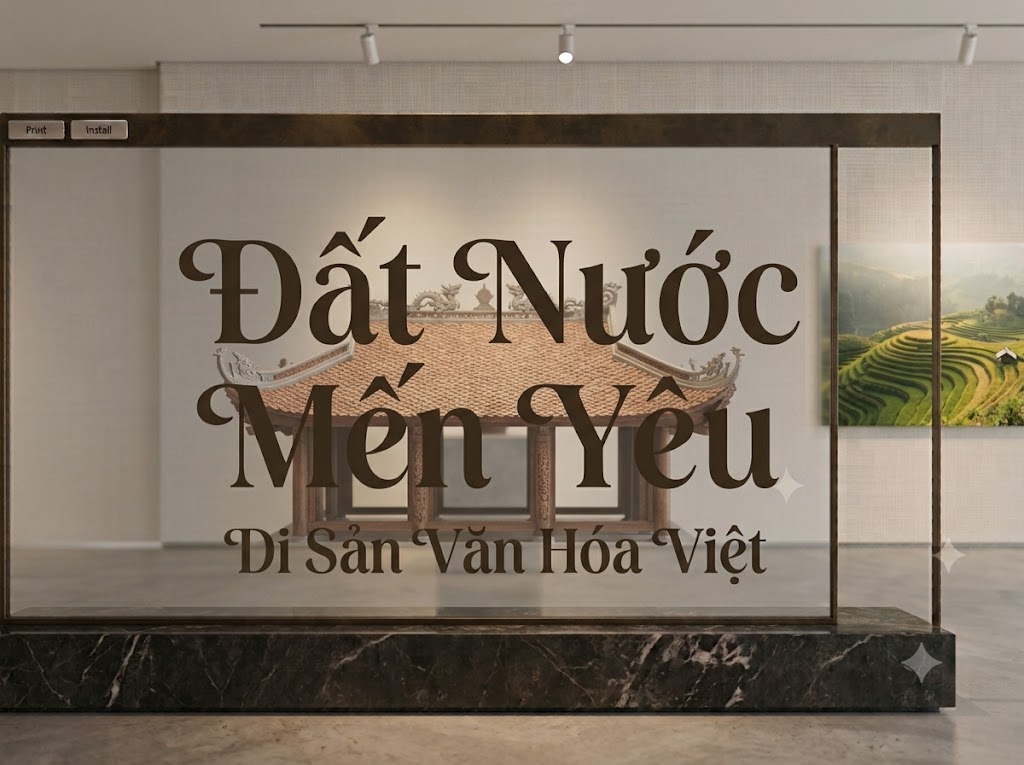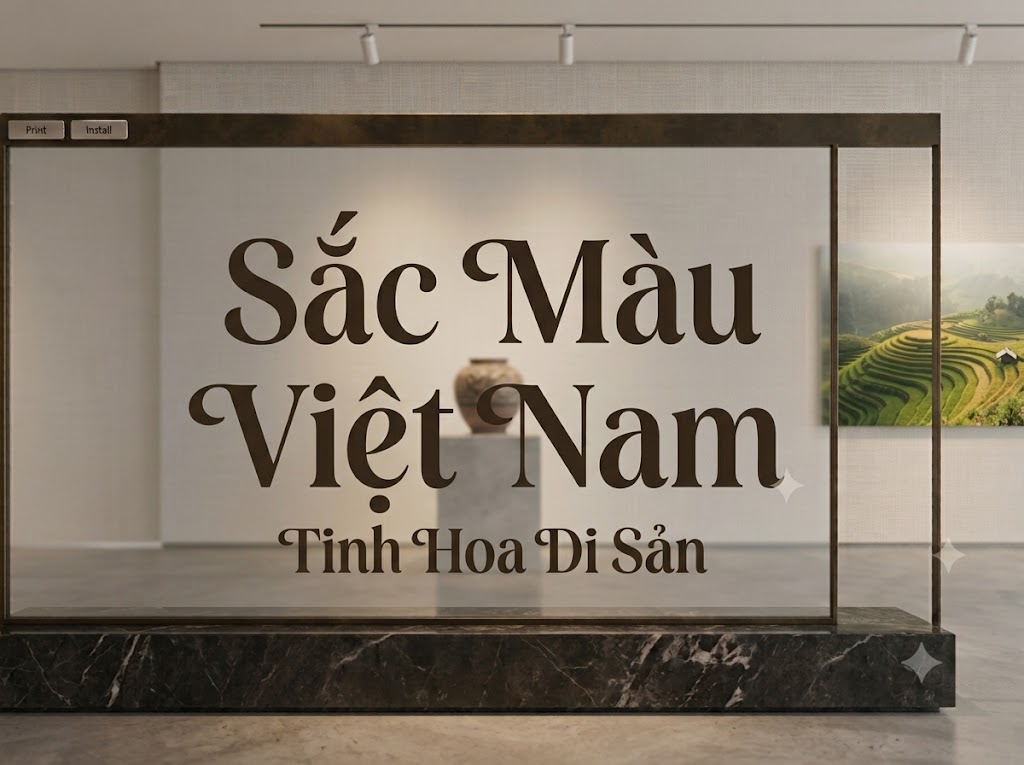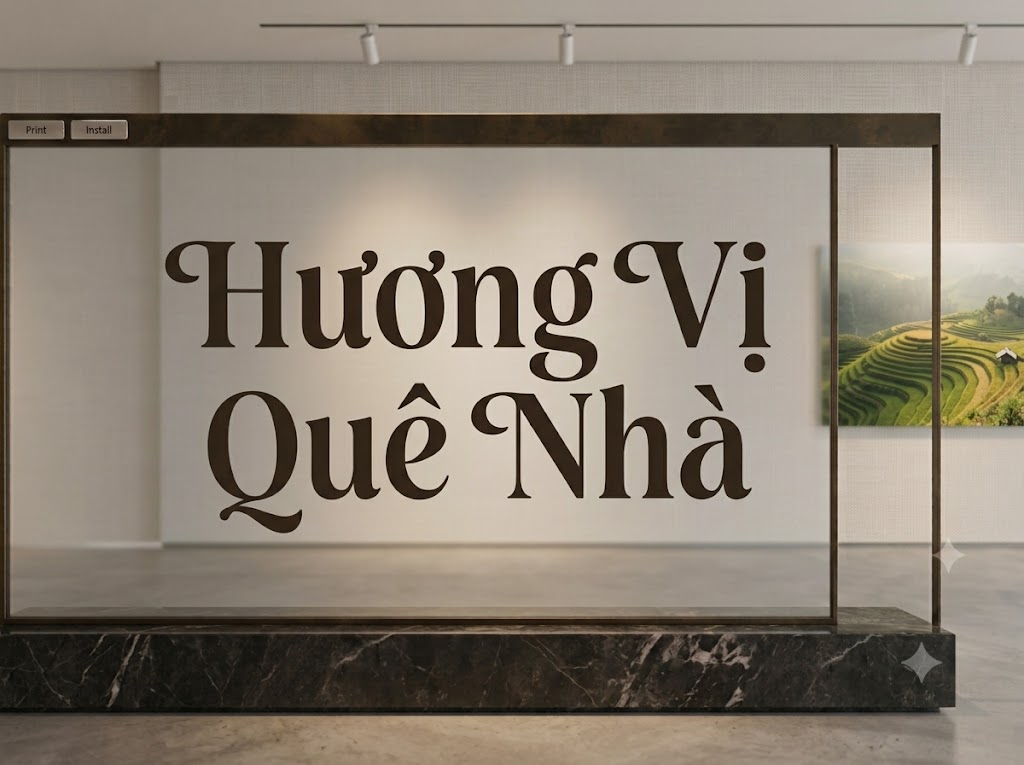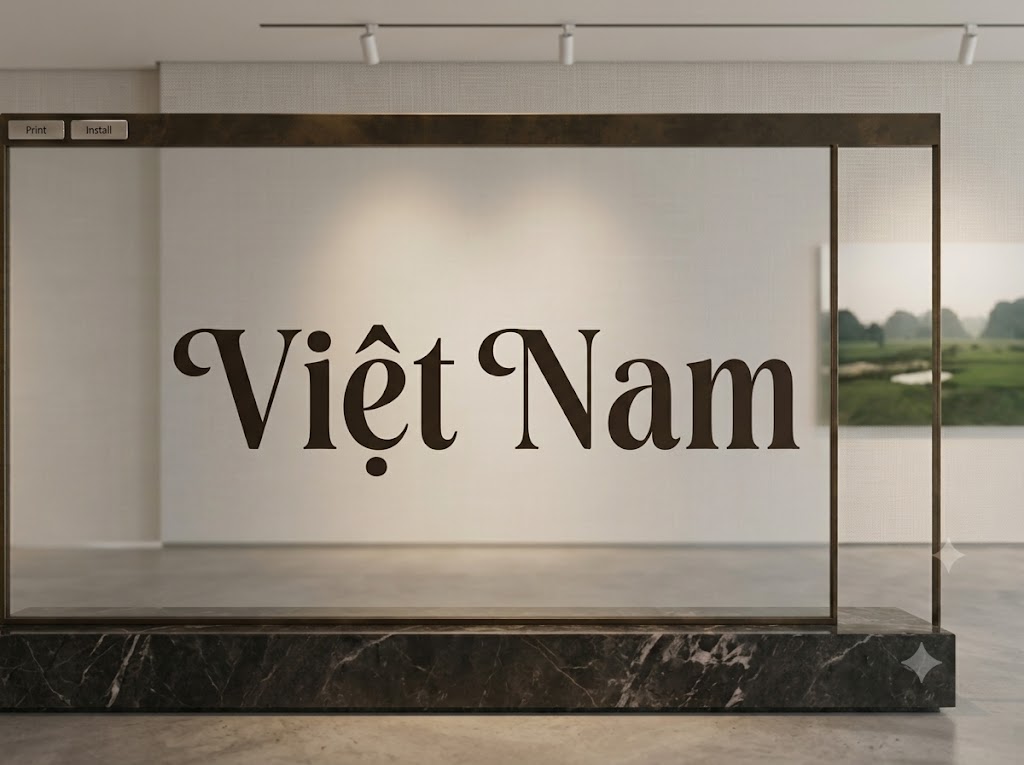
1FTV VIP Arkosic
Giữa vô vàn các phông chữ hiển thị (display font) trên thị trường, nhóm chữ mang phong cách Modern Serif với độ tương phản cực hạn luôn là biểu tượng trường tồn của sự xa xỉ, sang trọng và tư duy mỹ thuật đẳng cấp.
Một dòng tiêu đề được lựa chọn phông chữ tinh tế không chỉ làm nhiệm vụ truyền tải thông tin đơn thuần, mà còn ngay lập tức định vị giá trị cao cấp cho toàn bộ ấn phẩm quảng cáo hoặc thước phim của bạn.
Nếu bạn đang tìm kiếm một bộ chữ có chân mang phom dáng thuôn gọn thanh lịch, sở hữu những đường nét nhấn nhả đầy kiêu kỳ để làm mới các dự án truyền thông của mình, thì font 1FTV VIP Arkosic chính là một lựa chọn hoàn hảo.
Giới thiệu về font 1FTV VIP Arkosic
Font 1FTV VIP Arkosic là một bộ chữ hiển thị có chân (serif display) được thiết kế theo trường phái tân cổ điển thời thượng, hướng tới phân khúc truyền thông cao cấp, thời trang và lookbook nghệ thuật.
Nhờ cấu trúc kỹ thuật đồng bộ này, phông chữ mang đến khả năng hiển thị vô cùng mượt mà, sắc nét, giúp bạn tự tin ứng dụng trên mọi phần mềm thiết kế đồ họa và biên tập video chuyên nghiệp mà không lo gặp lỗi vỡ nét khi phóng lớn.
Đặc điểm nổi bật của phong cách thiết kế VIP Arkosic
Sức hút mê hoặc của font 1FTV VIP Arkosic đến từ cấu trúc hình khối thuôn dài (condensed) kết hợp hài hòa với vũ điệu nét thanh nét đậm cực kỳ sắc sảo:
Độ tương phản cực hạn (High Contrast): Điểm đắt giá nhất của Arkosic là sự chênh lệch vô cùng lớn giữa nét dọc siêu dày (stems) và nét ngang siêu mảnh (hairlines). Sự tương phản mạnh mẽ này tạo nên một hiệu ứng thị giác đầy kịch tính, sang trọng, gợi liên tưởng đến trang bìa của các tạp chí thời trang danh tiếng toàn cầu như Vogue hay Harper’s Bazaar.
Phom dáng thuôn gọn dọc thanh lịch: Dáng chữ được thiết kế bóp gọn theo chiều ngang, giúp bạn dễ dàng sắp xếp các dòng headline dài vào không gian hẹp mà vẫn giữ được kích thước chữ lớn, không bị tràn viền hay phá vỡ bố cục chung.
Hỗ trợ hệ ký tự hoa – thường đồng bộ: Khác với nhiều dòng font luxury chỉ hỗ trợ chữ in hoa, 1FTV VIP Arkosic tích hợp trọn vẹn cả hệ thống chữ cái thường và chữ viết hoa đồng bộ. Các nét uốn giọt nước ở chữ thường kết hợp với phần chân chữ (serif) sắc sảo tạo nên một nhịp điệu đọc vô cùng thoáng đãng, uyển chuyển và tự nhiên.
Hệ thống khoảng cách chữ (kerning) và độ giãn dòng (tracking) đã được căn chỉnh chuẩn xác đến từng pixel, giúp các nét chữ siêu tương phản khi đứng cạnh nhau luôn giữ được khoảng trống thẩm mỹ lý tưởng, tạo cảm giác ngăn nắp và vô cùng dễ chịu cho mắt người đọc.
Tích hợp đầy đủ bộ chữ cái hoa – thường, dãy chữ số từ 0-9 dáng khối đứng thanh lịch cùng hệ thống các ký tự đặc biệt, dấu câu thông dụng (
Bản Việt hóa chuẩn chỉnh từ đội ngũ 1FTV giúp các nhà sáng tạo nội dung hoàn toàn yên tâm thiết kế các văn bản tiếng Việt có dấu phức tạp mà không lo gặp phải tình trạng lỗi hiển thị dấu câu hay nhảy font khó chịu.
Hình ảnh demo thực tế của font 1FTV VIP Arkosic
Để giúp bạn dễ dàng hình dung khả năng co giãn và hiển thị linh hoạt của phông chữ này trên các kích thước khác nhau:
Kích thước nhỏ (12pt – 24pt): Dù sở hữu các đường nét thanh mảnh có độ tương phản lớn, cấu trúc chữ đứng và bộ chữ thường vẫn hiển thị rất rõ ràng, ngay ngắn, tạo trải nghiệm đọc mượt mà trên các giao diện hiển thị di động.
Kích thước lớn (36pt – 72pt): Đây là đất diễn lý tưởng nhất để font chữ phô diễn toàn bộ sự kiêu sa, quý phái của các đường nét vát nhọn và nét dọc siêu đậm, tạo hiệu ứng thị giác đỉnh cao chiếm trọn sự chú ý cho các dòng headline chính.
Ứng dụng của font Arkosic trong thiết kế đồ họa và làm video
Sở hữu nét cá tính sang trọng, quý phái và cấu trúc hình khối thuôn gọn tinh tế, font 1FTV VIP Arkosic mở ra không gian ứng dụng vô cùng rộng lớn cho các dự án truyền thông hiện đại:
Làm tiêu đề cho video ngắn (TikTok, Reels, Shorts): Kiểu chữ serif dáng thuôn gọn này hiển thị vô cùng ấn tượng trên các khung hình đứng tỷ lệ 9:16 của thiết bị di động. Độ mảnh mai và ráo hoảnh của chữ giúp dòng giật tít hiển thị một cách tự nhiên, cuốn hút người xem lướt feed dừng lại ngay lập tức mà không che mất chủ thể chính của video thời trang, mỹ phẩm hay vlog phong cách sống.
Thiết kế bìa tạp chí, Lookbook và Poster nghệ thuật: Hoàn hảo cho các ấn phẩm truyền thông thuộc lĩnh vực thời trang xa xỉ, mỹ phẩm cao cấp, trang sức, kiến trúc đương đại hoặc các triển lãm nghệ thuật sang trọng.